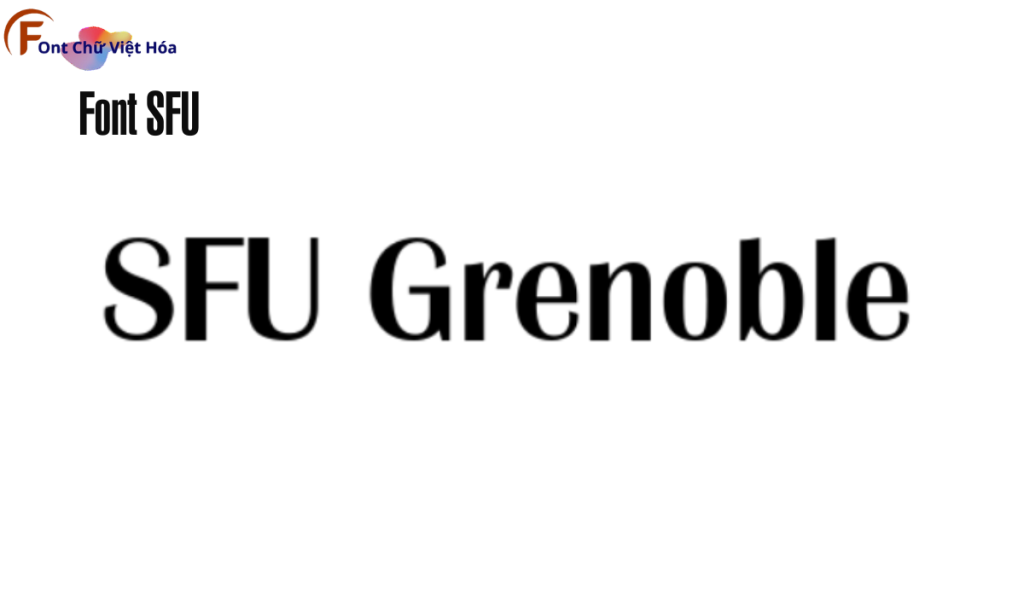
Font SFU Grenoble Việt Hóa
Tác giả: SFU
Bộ Font: SFU
Kiểu chữ: Có chân
Font SFU Grenoble Việt Hóa, thuộc bộ font SFU, là sự lựa chọn hoàn hảo cho những ai yêu thích phong cách serif hiện đại với các đường nét mạnh mẽ và cá tính. Font này được thiết kế nhằm mục tiêu tạo ra sự rõ ràng và dễ đọc, đặc biệt phù hợp cho các thiết kế như poster, logo, và tiêu đề. Đặc điểm hình dạng của SFU Grenoble là các đường nét đậm và tỷ lệ chữ cân đối, giúp tạo ấn tượng thị giác mạnh mẽ và sự rõ ràng trong từng chi tiết. Font này cũng đã được Việt hóa, mang đến sự linh hoạt và tiện dụng cho các dự án thiết kế bằng tiếng Việt, giúp người dùng dễ dàng tiếp cận và sử dụng.